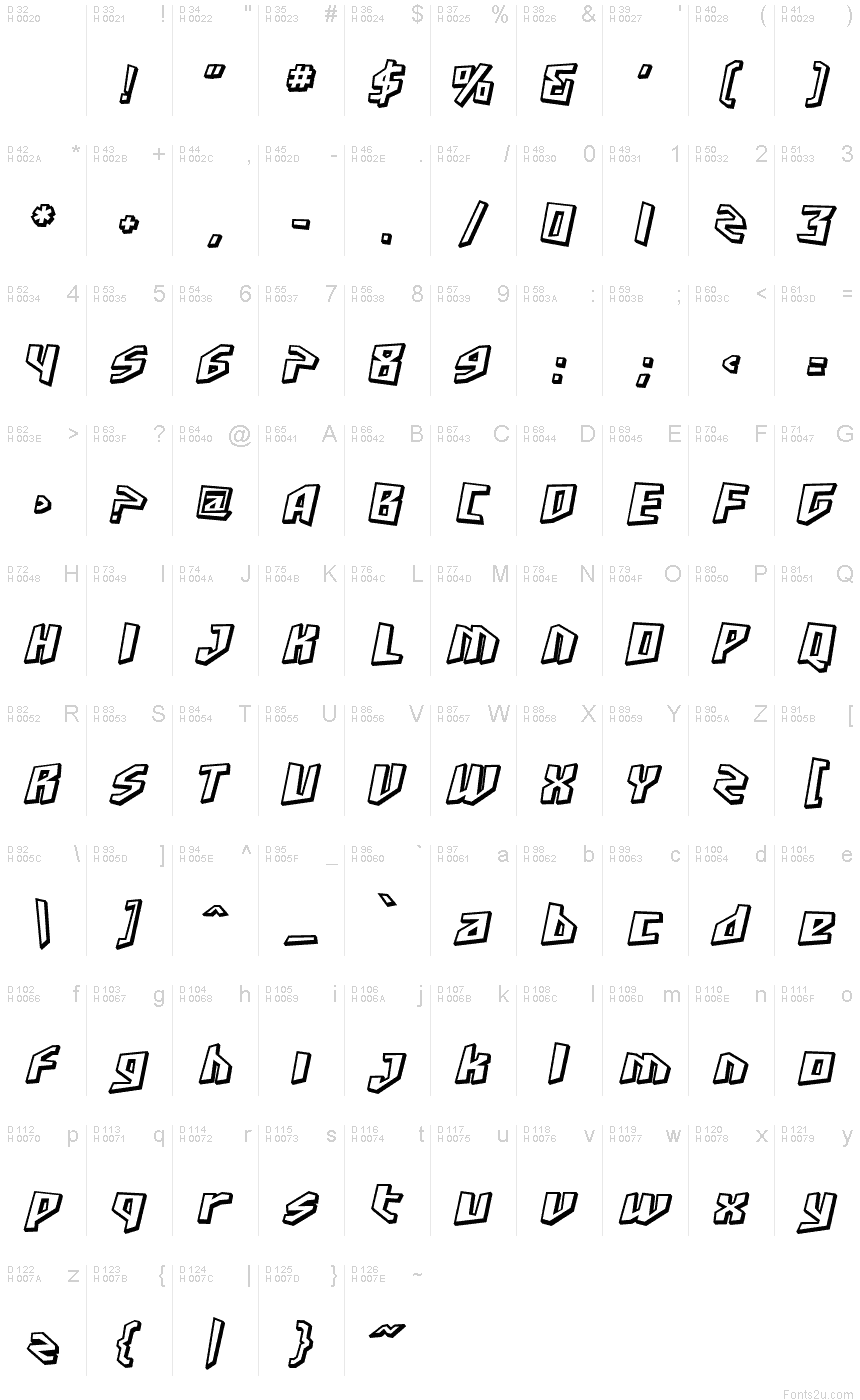
SF Junk Culture Shaded Oblique od ShyFoundry to darmowy, cieniowany font typu display o pochyłym kroju, utrzymany w komiksowym, surowym stylu z wyrazistymi krawędziami 3D. Litery są mocno pochylone i zazębiają się dzięki ściętym rogom, grubym konturom oraz blokowemu cieniowaniu, co nadaje całemu krojowi surowy, plakatowy charakter.
Najlepiej sprawdza się tam, gdzie tytuł potrzebuje pazura, a nie wygładzenia: w grafikach skejtowych i streetwearowych, na okładkach zinów, w oprawie mixtape’ów, plakatach w stylu arcade czy krótkich logotypach. Jako darmowy font, świetnie nadaje się też do odważnych nagłówków, plansz tytułowych i szybkich projektów brandingowych, zwłaszcza gdy to ukośne cieniowanie wykonuje większość wizualnej roboty.
Prezentacja i próbka wizualna czcionki SF Junk Culture Shaded Oblique